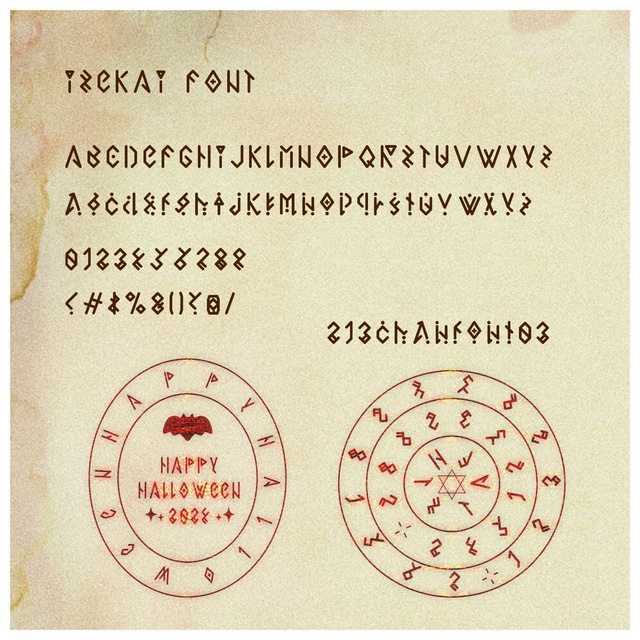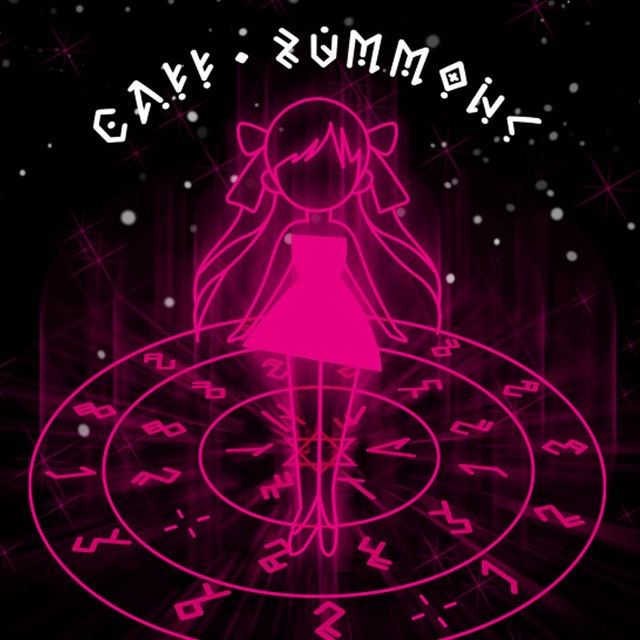
isekai_font【商用可】
このisekaiフォントは213ちゃんが作った3個目 商用可のフリーフォント(freefont)です。 読めちゃう異世界フォントです。 魔法陣やハロウィン、クリスマスにオススメ!!! 印刷物・ゲームやWeb、YouTubeのサムネイルやタイトルデザインなどにいかがでしょうか? 基本フリーですが、当フォントを利用した制作物などを、SNSで教えてくれると励みになります。 制作時のお気に入りポイントをnoteで記事にしています。 ぜひ遊びにきてね!スキ!お待ちしています。 https://note.com/sweet_2727/n/nc208fb28bc1c 【収録内容】アルフファベット(大文字・小文字)・少しの記号 【Readme】フォントご使用上の注意 ・フォントの著作権は、213ちゃんに帰属します。 ・可愛がってくださるとうれしいです。 ・無断転載・再配布は堅くお断りいたします。 ・DLしたフォントに起因する損害は補償致しかねますので予めご了承ください。 ・使用する際の不明点はお問い合わせ先にご連絡ください。答えられる範囲でお返事いたします。